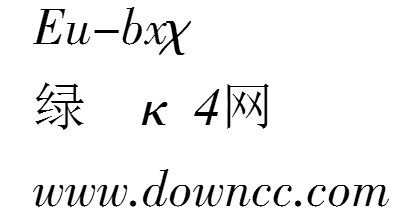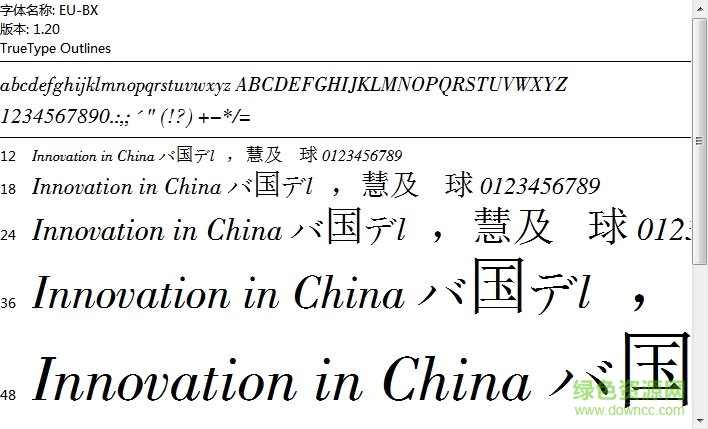
Eu-bx字體是方正字庫(kù)推出的一款教材字體,字體分布范圍較廣,中文采用了日文字體的書(shū)寫(xiě)格式,英文流暢有格調(diào),常用在photoshop等軟件中,讓設(shè)計(jì)更為出彩,綠色資源網(wǎng)誠(chéng)意推薦!
eu bx字體共有7525個(gè)字符,分布范圍較廣,能很大程度滿足大家的日常需求,是eu字體家族的特色字體,是國(guó)內(nèi)的數(shù)學(xué)教材數(shù)學(xué)字體。
eu bx字體并不是一款常規(guī)意義上的英文字體或中文字體,講部分中文變成日文,而需在日文輸入法下才能顯示清晰,所以屬于日本文字的范疇。